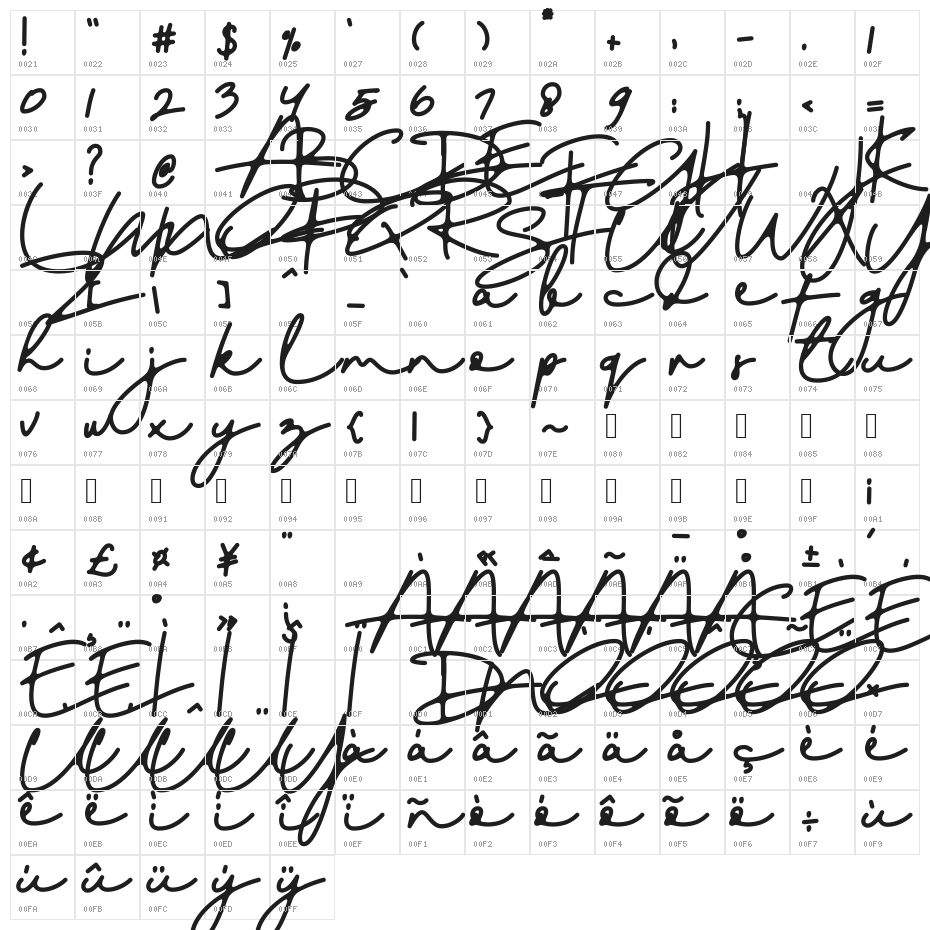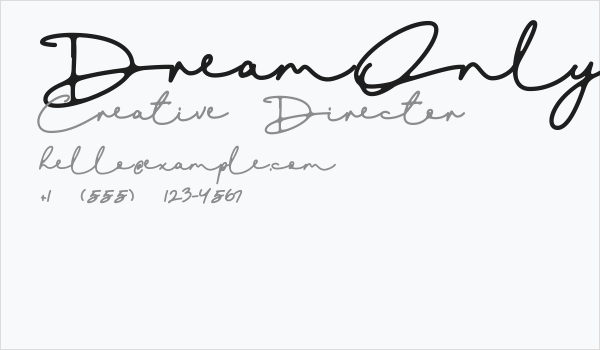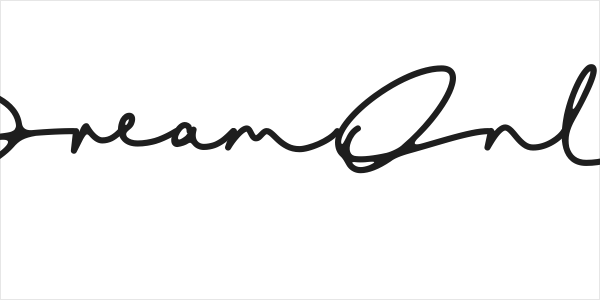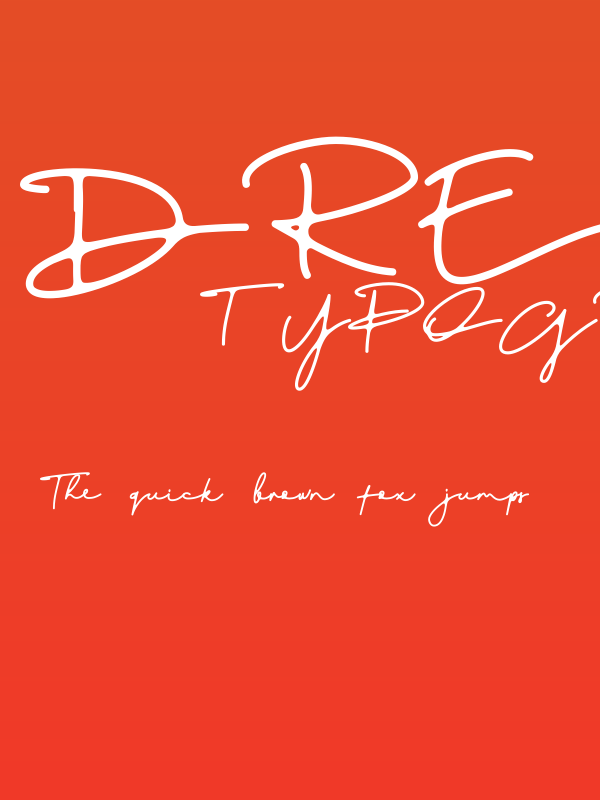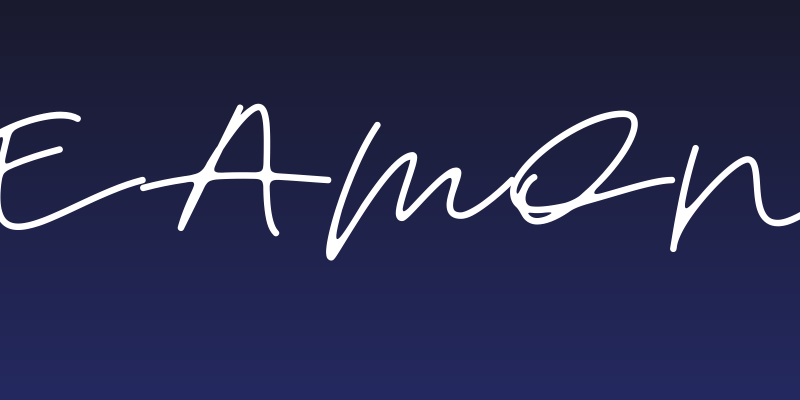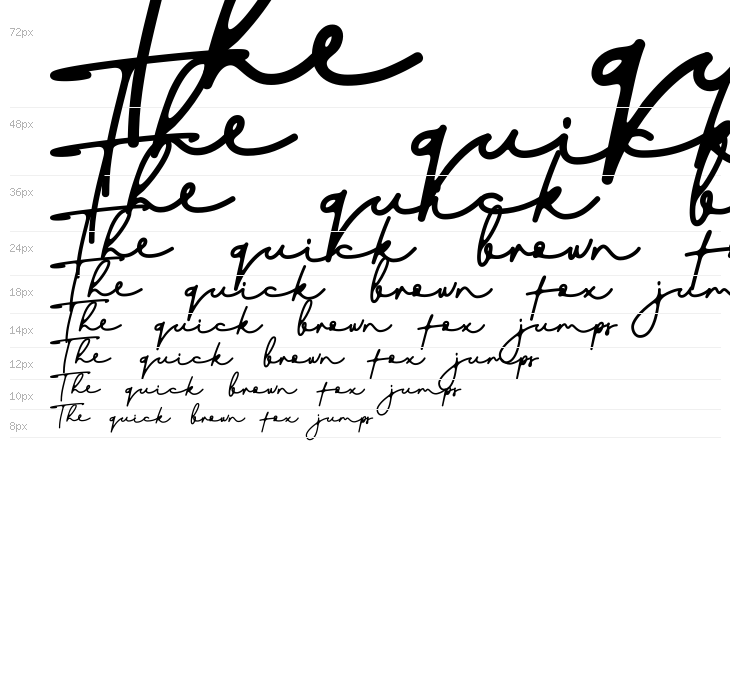
DreamOnly Font
| Stile generale | Casual, Elegant |
| Caso d'uso | Logos, Invitations, Greeting Cards |
| Progetti proposti | Ideal for invitations, greeting cards, personal branding, and any project needing a warm, approachable feel. |